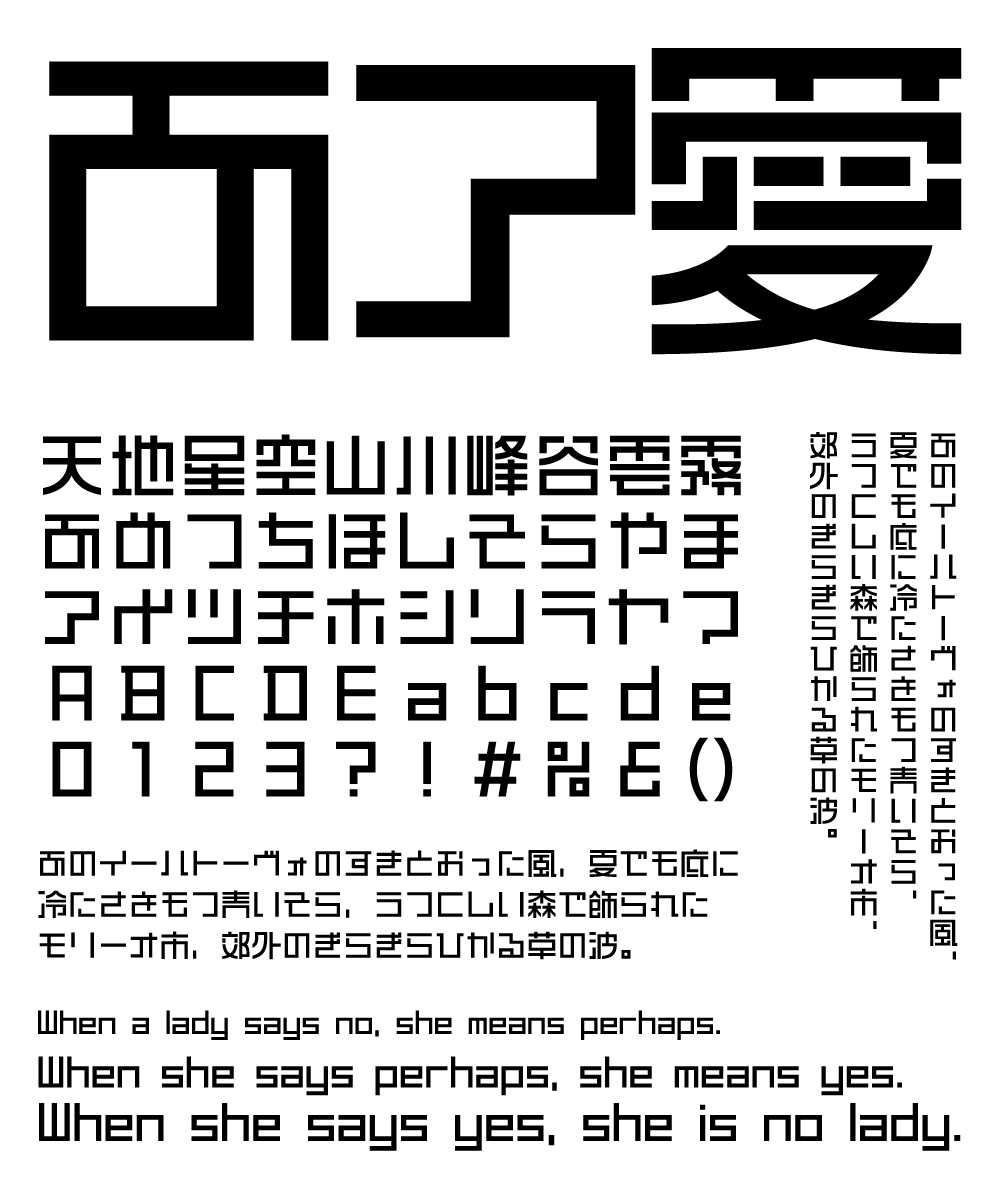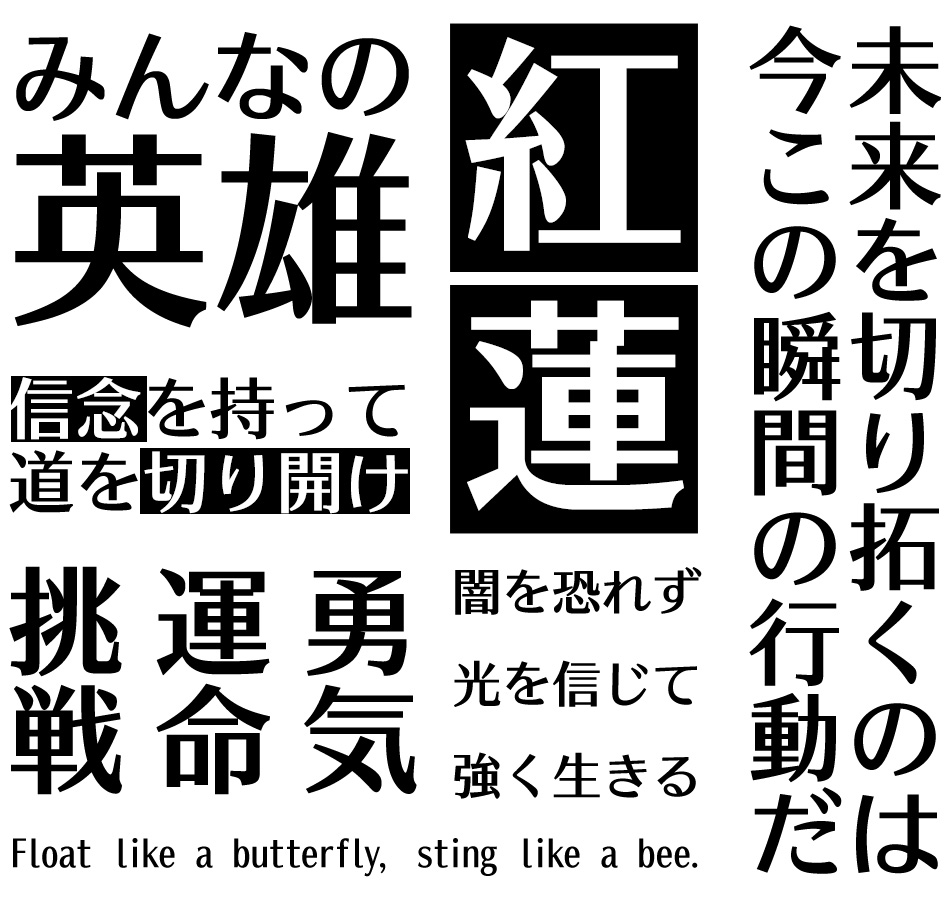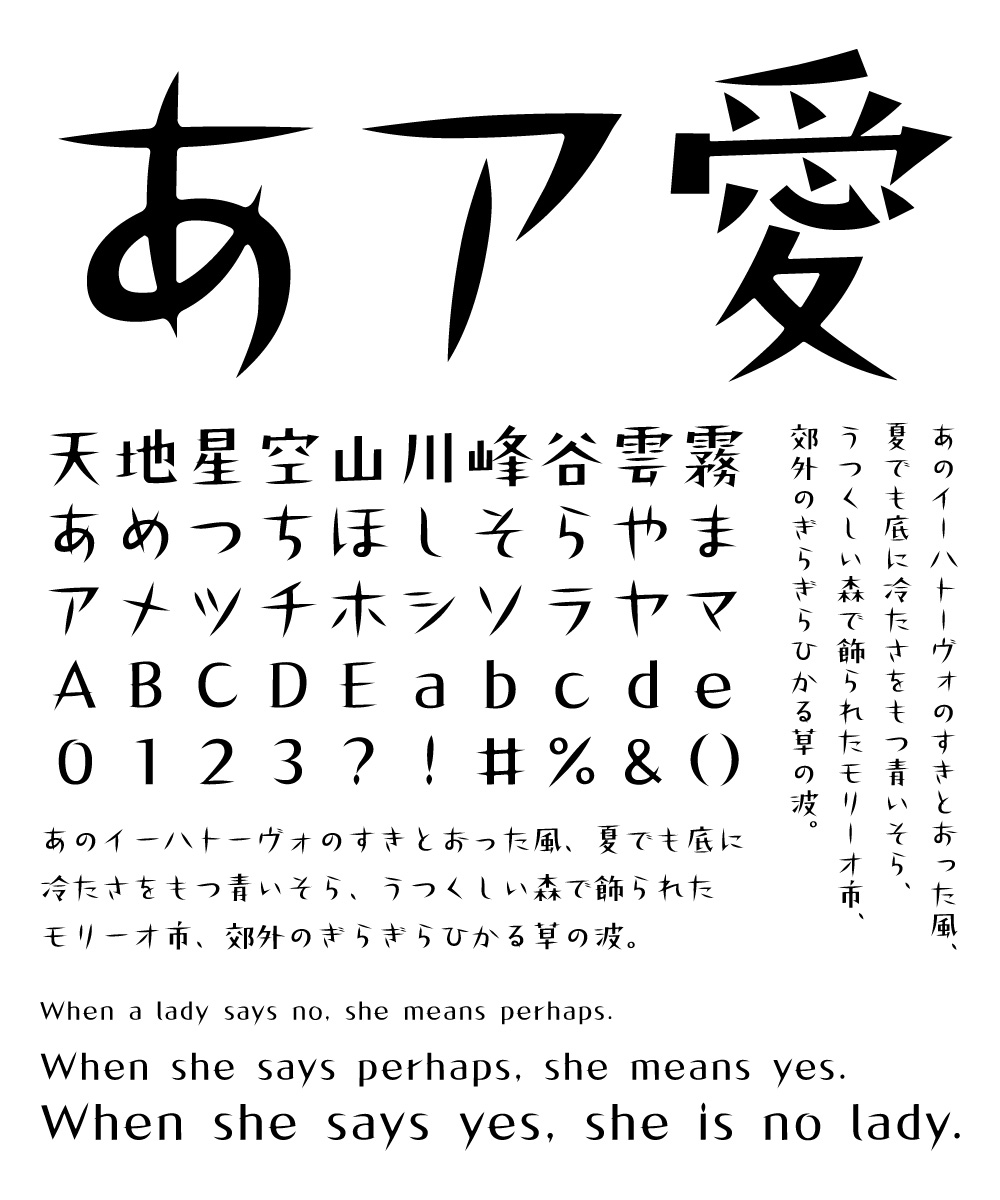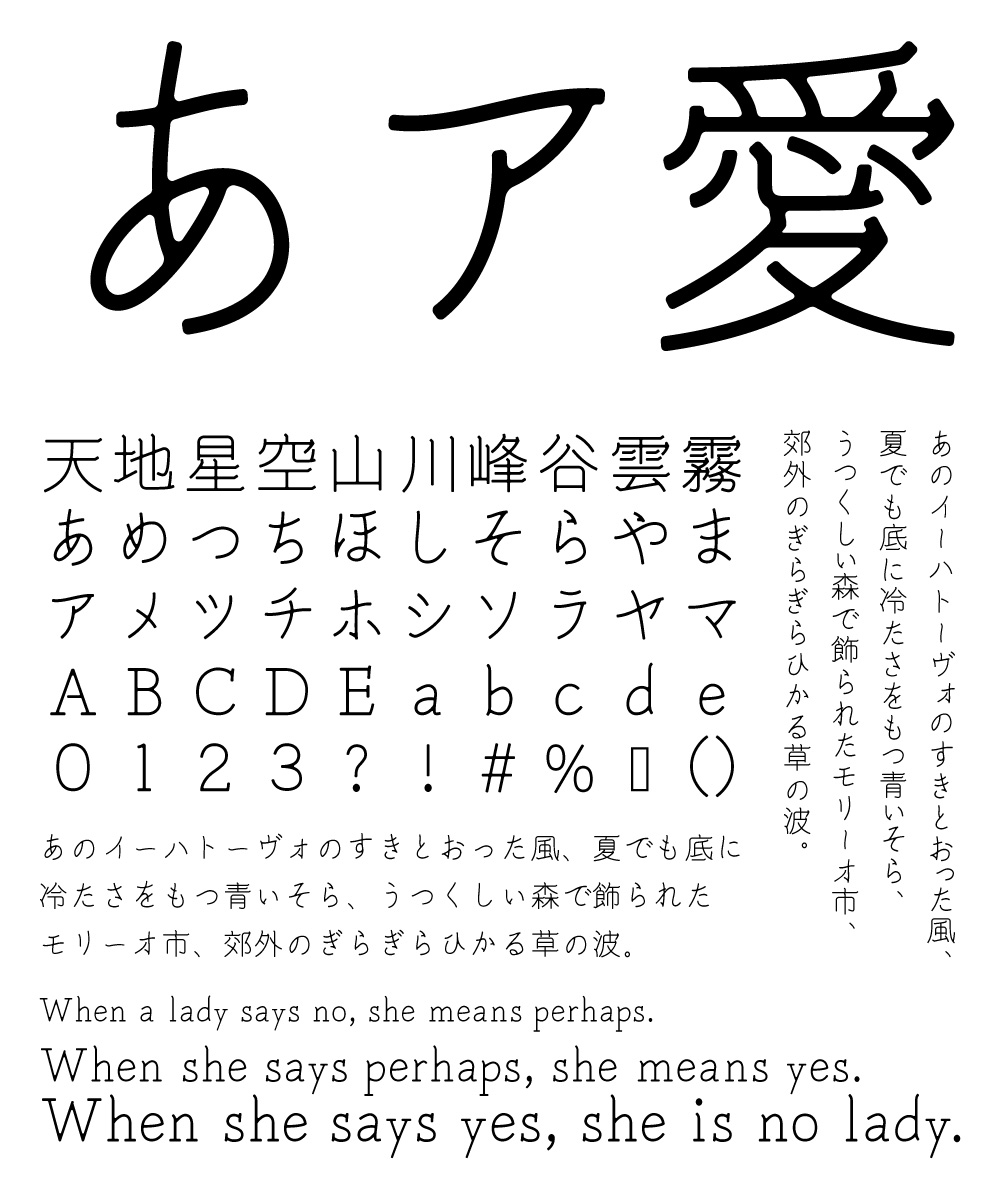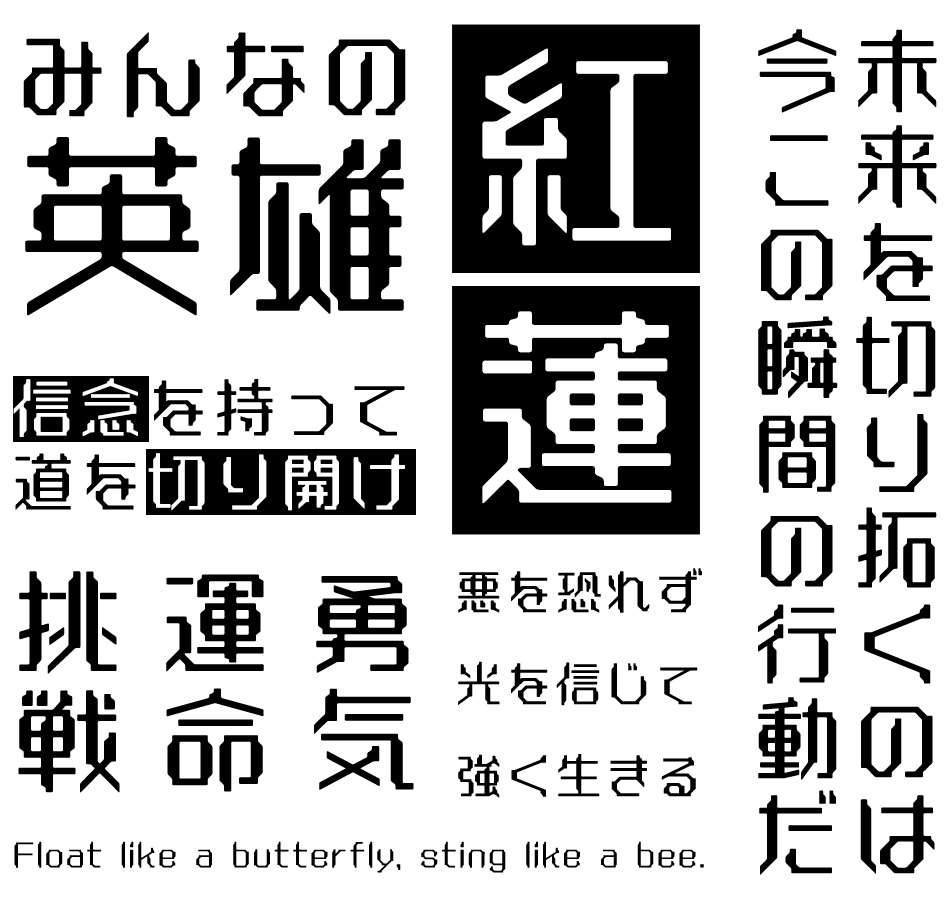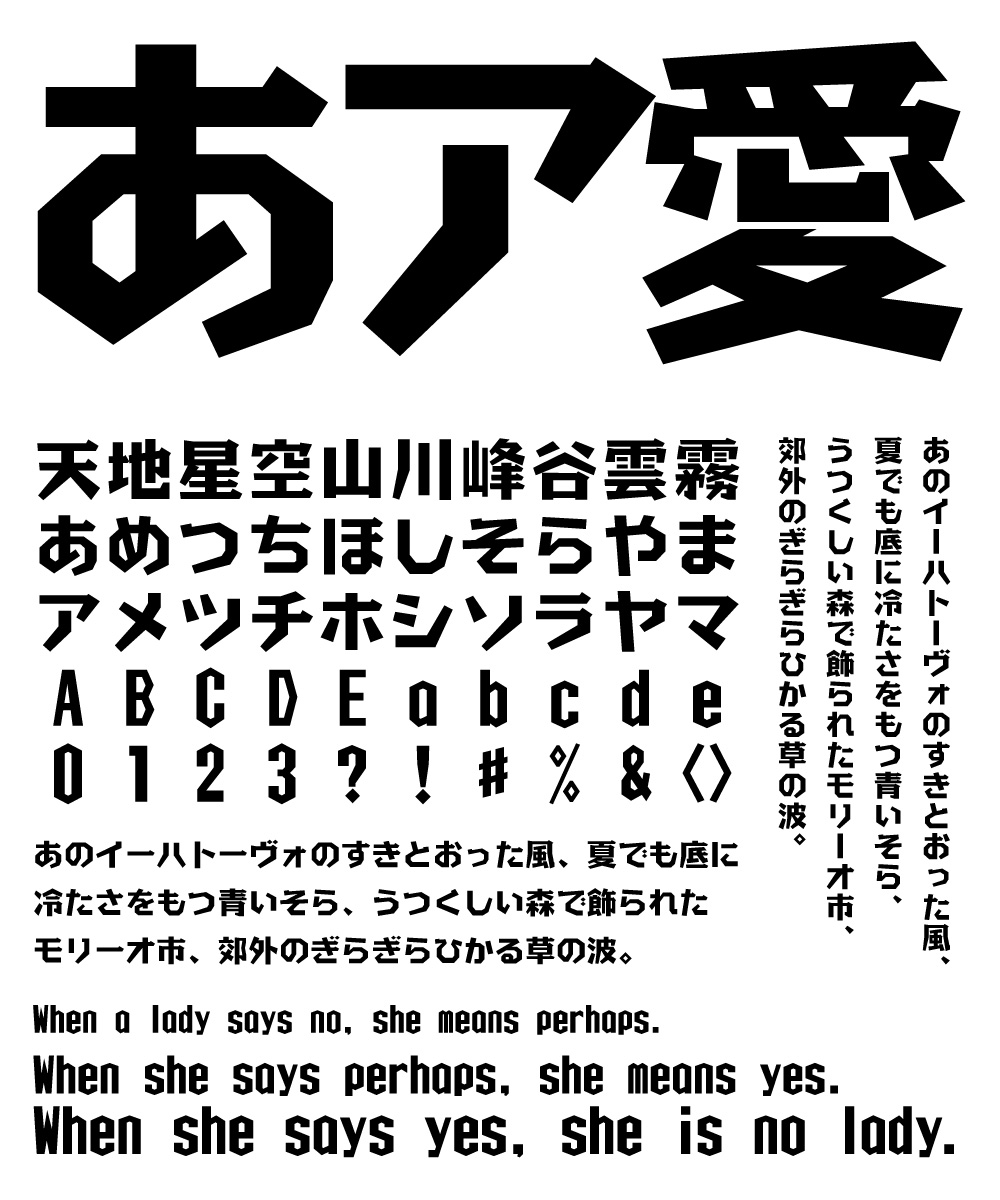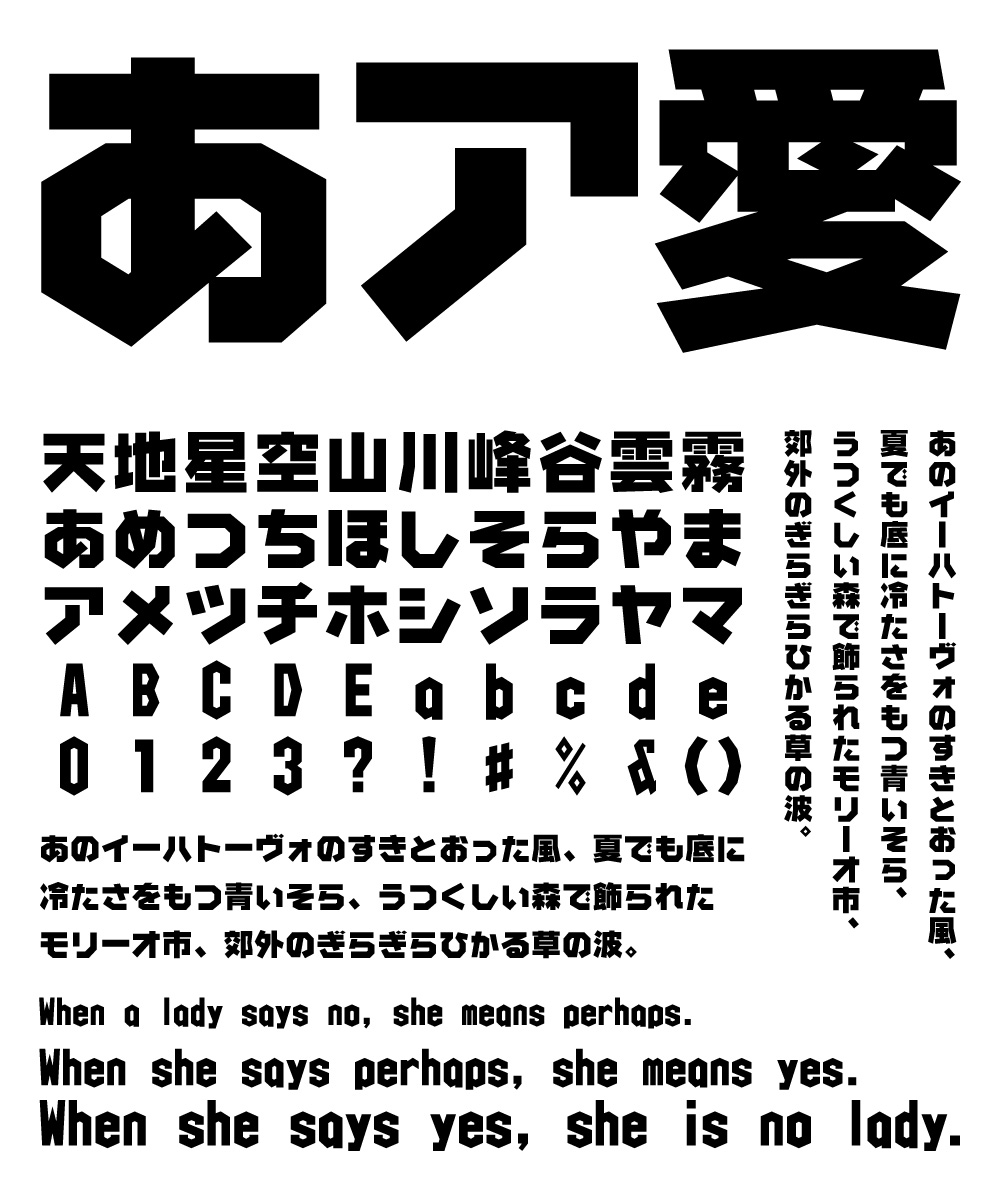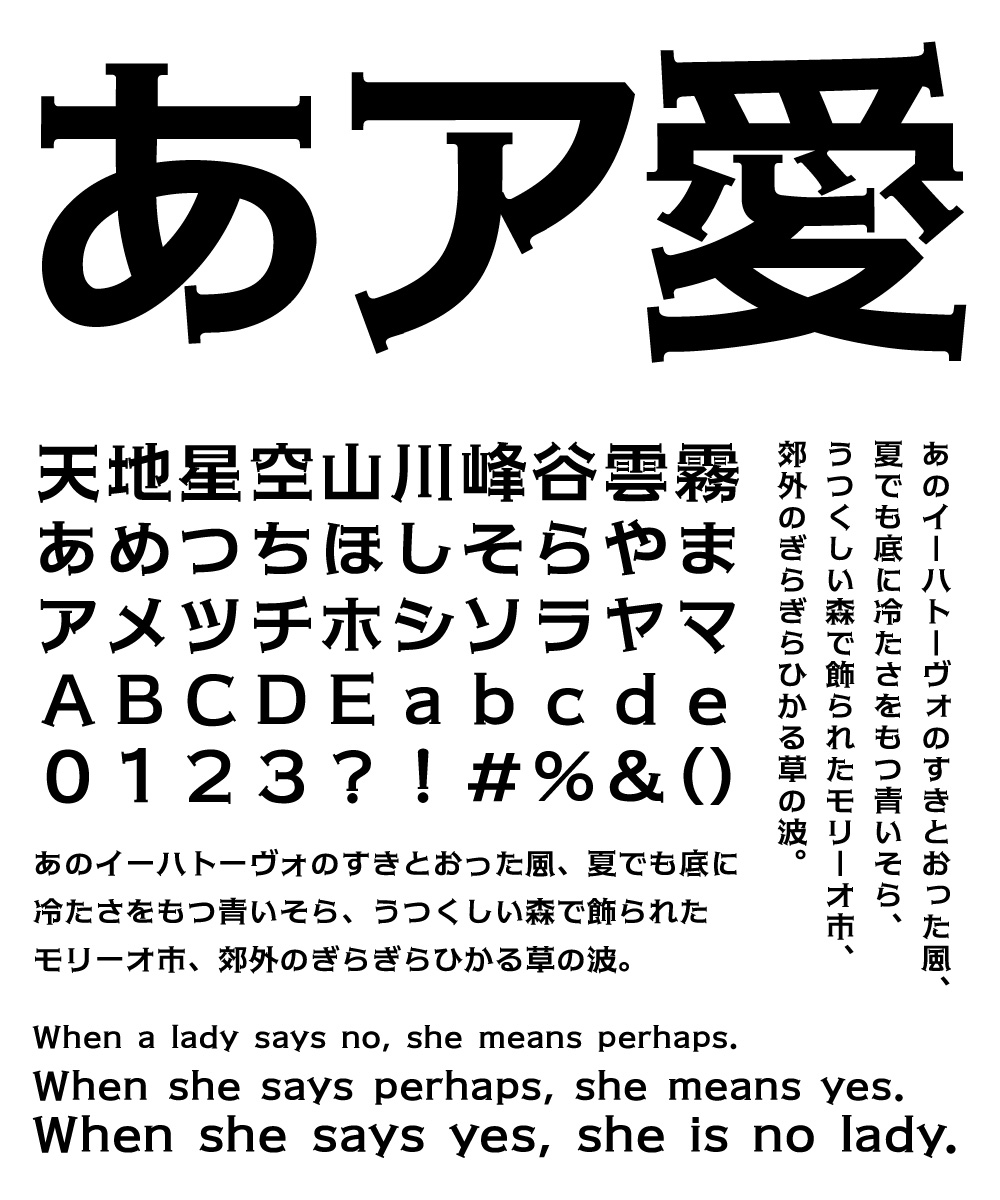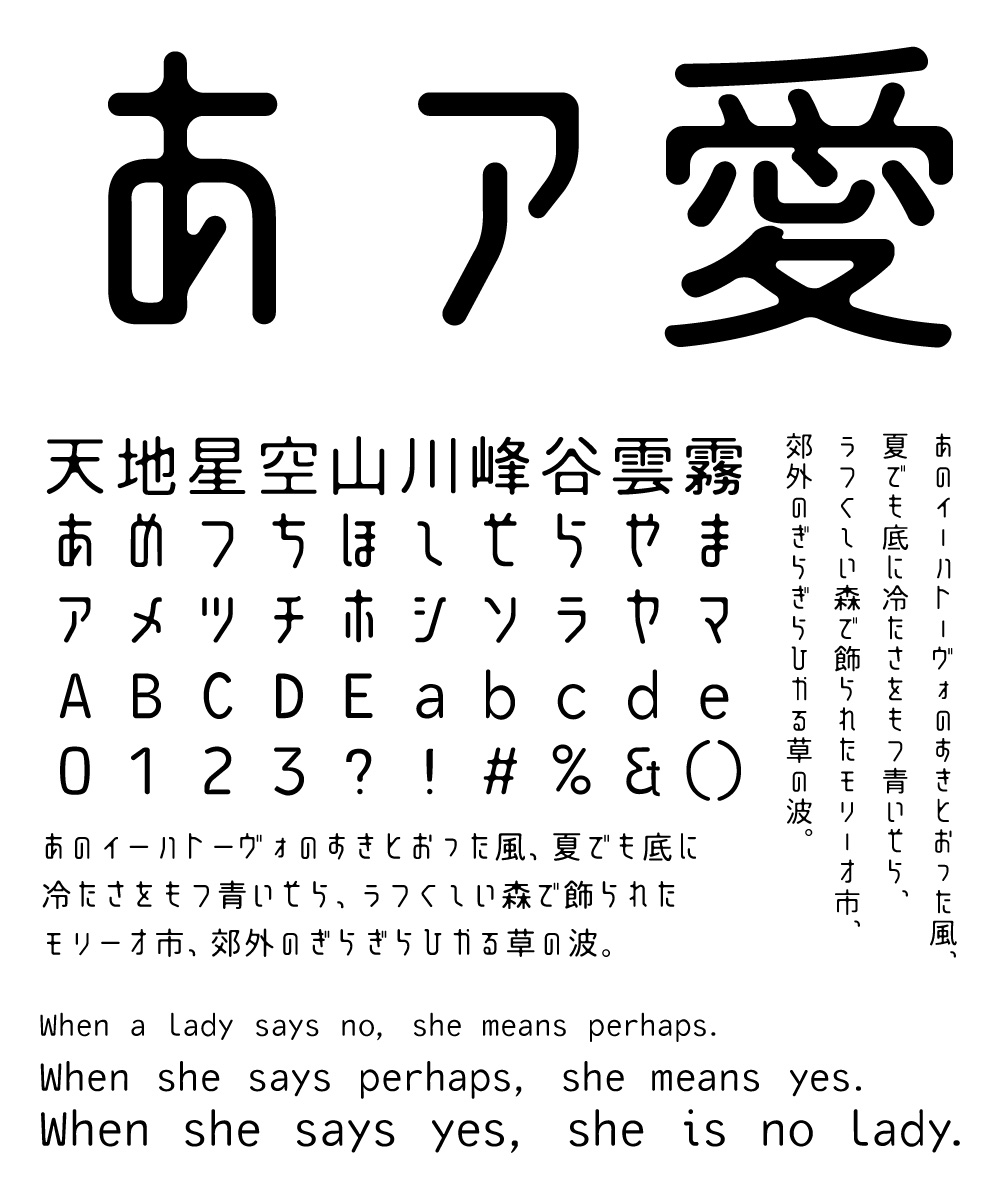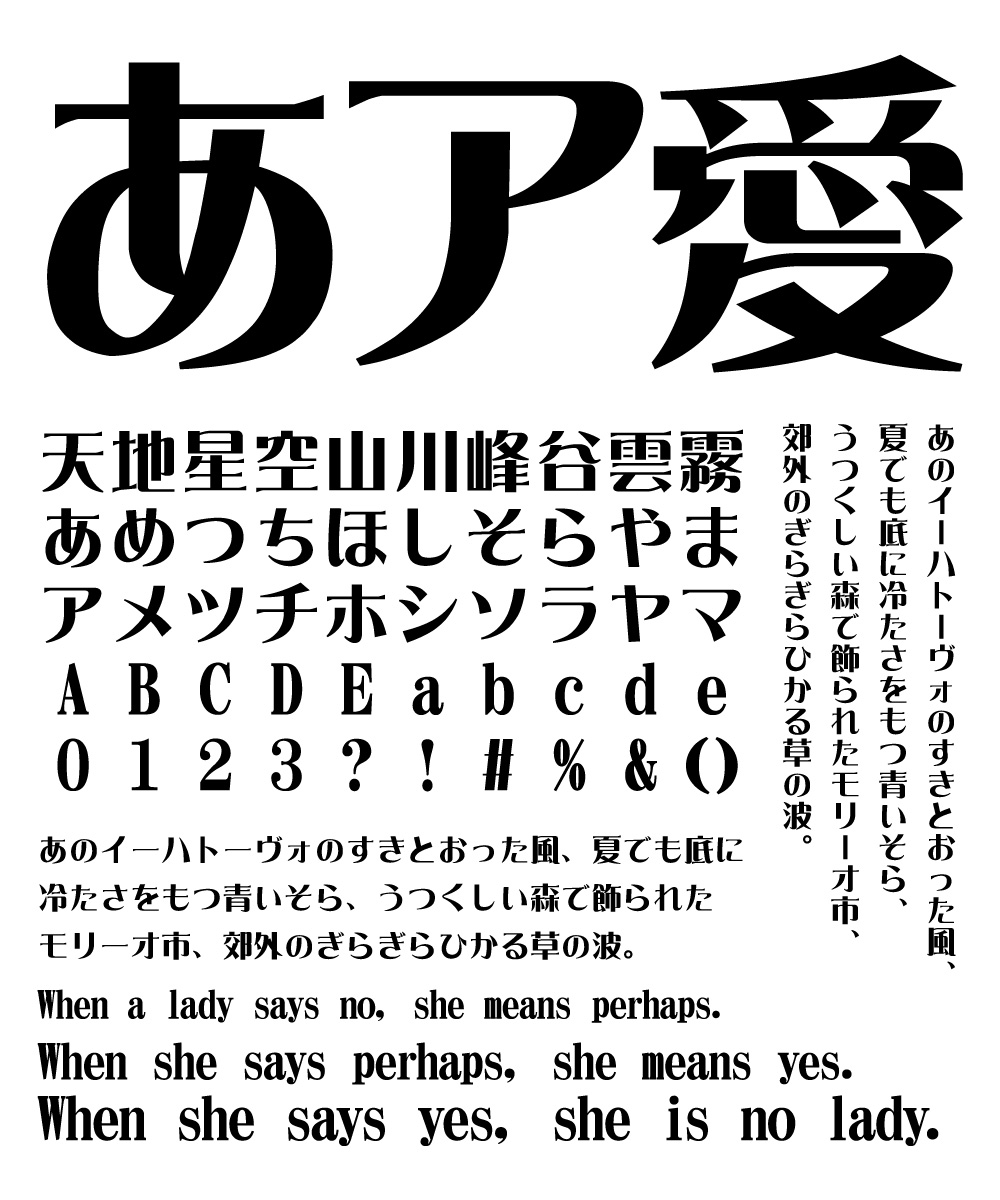
カッコいいフォント特集 オススメの“カッコいい”日本語フォントをご紹介!
日本語フォントはデザインにおいて重要な役割を果たします。特にカッコいい日本語フォントは、デザイン全体の印象を大きく左右し、視覚的なインパクトを強めます。本特集では、カッコいい日本語フォントの主要な特徴とその魅力について詳しくご紹介します。
カッコいいフォントの特徴
カッコいい日本語フォントを使用することで、デザインの質が格段に向上します。以下では、カッコいい日本語フォントの3つの主要な特徴について詳しく説明します。
カッコいいフォントの特徴とメリット
洗練されたデザイン
カッコいい日本語フォントの第一の特徴は、その洗練されたデザインです。モダンでシャープな線とバランスの取れたプロポーションが特長であり、直線と曲線の調和が取れているデザインは視覚的に非常に魅力的です。これにより、現代的なデザインプロジェクトやブランドイメージの構築に最適です。
ユニークなテクスチャ
特に目立たせたいデザインに最適なのが『ユニークなテクスチャ』です。東亜重工 GRUNGEの荒々しい感じや、DFひびゴシック体のひび割れ模様がその代表例です。このようなデザインは、とても印象的で、人の目を引きやすいです。広告やポスター、ブランドロゴなどで使うと、特別な雰囲気を演出し、デザイン全体を引き立てます。これにより、メッセージを効果的に伝えることができます。
個性とユニークさ
最後に、カッコいい日本語フォントは個性とユニークさを持っています。独特の筆遣いやオリジナルのデザイン要素が加わり、他のフォントと一線を画す存在感を持っています。これにより、特定のブランドやプロジェクトに独自の雰囲気やスタイルを付加することが可能です。個性的なフォントは視覚的なインパクトを強め、記憶に残りやすいデザインを実現します。
1. 東亜重工/GRUNGE
2. イワタミンゴ
3. DSフラミング
4. DS風流
5. DSストロング
6. きなりゴシック
7. 金魚ランタン
8. TA DON
9. TA-24H
10. TA-方縦
11. TA-クワドラ
12. DFロマン輝
13. DF金文ゴシック体
14. DF綜藝体
15. DF麗雅宋
16. DFひびゴシック体
17. モトヤステンシルアポロ
18. モトヤホンコン
19. JTCウインZM9
20. JTCウインZ1/Z5/Z10
21. 凛松体
22. 明朗体
23. 閃刃体
24. 蛍涼体
25. AFSセリフゴシック
26. FGPミライゴシック
27. KOさおとめ金陵
28. 闘龍
29. 京円
30. ファイトフォント
31. 酔虎
32. 忍者
33. JTC直線江戸文字「剣」
34. DF超極太楷書体
35. AR浪漫明朝体
36. まーと太角ゴシック
37. ガガガガ
38. F1-くりっぷM
39. F1-ラインボード
40. g_コミックホラー悪党
東亜重工 /GRUNGE
イワタ書体ライブラリー
東亜重工 /GRUNGE
カッコいいフォント 東亜重工
漫画家 弐瓶勉氏の原案・監修のもと、「東亜重工有限責任事業組合」と「株式会社イワタ」が共同で開発し、国内外で多くのファンを魅了する同氏の世界観をフォント化。
イワタミンゴ M/D/B/E/H
イワタ書体ライブラリー
イワタミンゴ M/D/B/E/H
カッコいいフォント イワタミンゴ
明朝体のシャープさ・可読性の良さと、ゴシック体の強さ・整斉さを加味した格調のある書体です。視認性を考慮して線間をあけ、明朝特有のウロコもありません。しかし、それでいながらゴシックとも雰囲気が全く異なります。
M/D/B/E/H の5ウェイト展開。商用印刷にも適する15,000以上の文字を収録したPro製品です。
DSフラミング
七種泰史/デザインシグナル
DSフラミング
カッコいいフォント DSフラミング
フラフラ + 明朝 + ハミング。フライ + 明朝 + グー。明朝体をベースにした軽やかで動きのあるフォント。パッと明るくなるような楽しい雰囲気を持ったデザインです。
DS風流
七種泰史/デザインシグナル
DS風流
カッコいいフォント DS風流
古典的な落ち着き、優雅さ、時の流れをイメージした書体です。
DSストロング
七種泰史/デザインシグナル
DSストロング
カッコいいフォント DSストロング
見出しやキャッチコピーにぴったり。岩石のような堅さ、力強さの中にも優しさを感じる、太く元気な書体です。